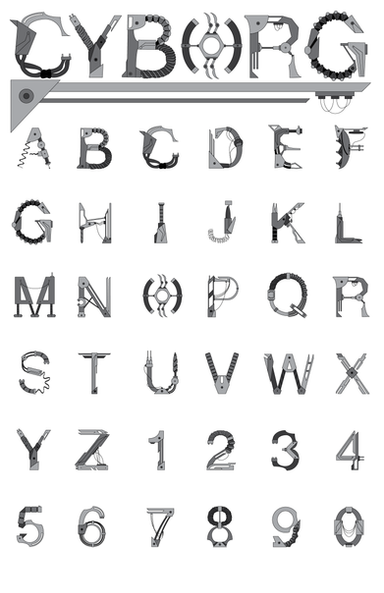
PORTUGUÊSEste foi um tipo de letra que desenhei para um dos primeiros trabalhos que fiz no meu curso em que tinhamos que "descobrir" letras em locais e objectos não habituais e a partir do qual fizemos uma T-shirt (que também ) vou publicar. Basea-se em objectos metálicos que encontrei e fotografei na oficina do meu irmão mais novo (sim ele tem uma oficina e quer ser mecânico) a maior parte deles peças de bicicletas e ferramentas.
This was a font I designed for one of the first works I made in my design degree. We had to find letters in non-usual places or objects and make a font that we used later to design a t-shirt (that I'me going to publish here too...). My font is based on metalic objects that I found and photografed in my younger brother's workshop (yes he has his workshop and wants to be a mechanic...) most of letters are made from parts of bikes and tools.